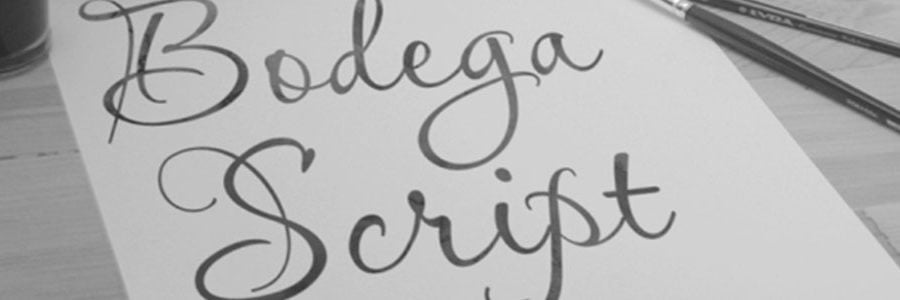
BODEGA SCRIPT : Typographie gratuite
Découvrez la nouvelle police de caractères stylisés à la main BODEGA SCRIPT, parfaite pour créer un texte authentique à la main avec une base de danse, une touche classique et élégante.
Bodega Script peut être utilisée à diverses fins : les titres, la signature, les logos, l’invitation de mariage, l’impression sur t-shirt, le papier à en-tête, la signalisation, l’emballage des produits, les lettres, les nouvelles, les affiches, les citations manuscrites, brochures etc.